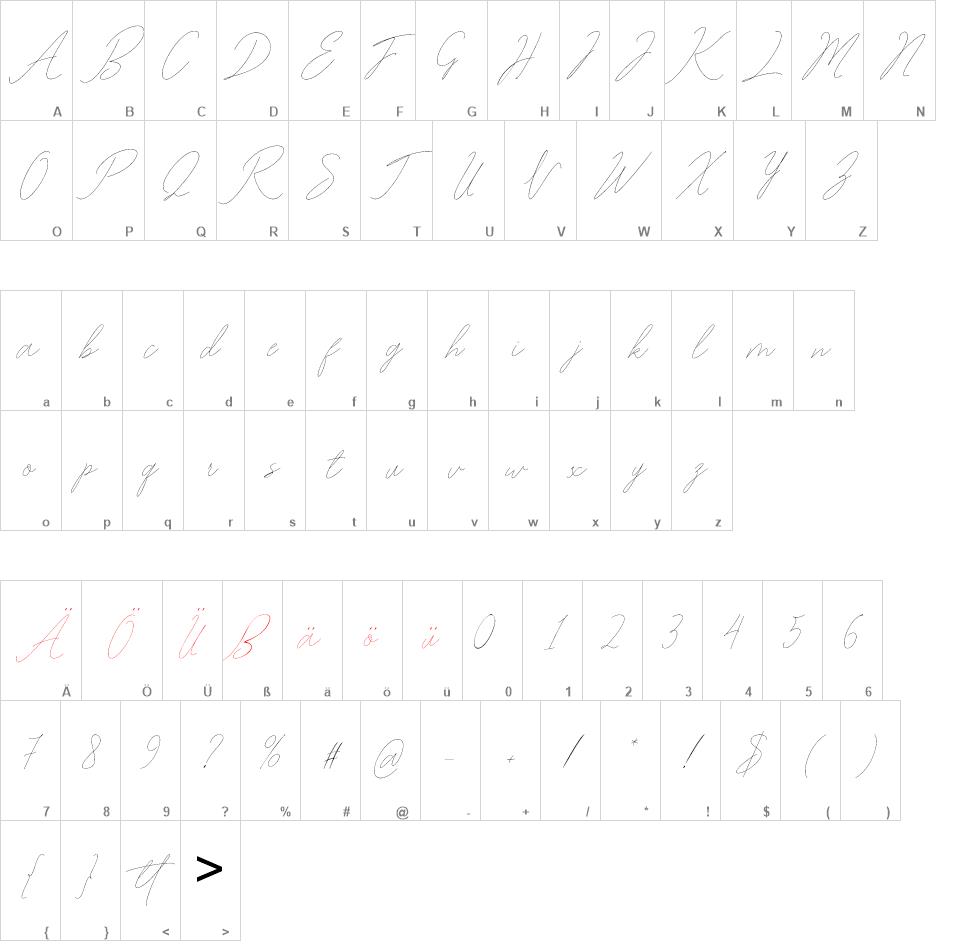
Washington
Washington font
Washington
Washington ist eine Unterschrift Schriftart, die die charakteristische Handschrift hat, ist es sehr geeignet, bestimmte Etiketten-und Event-Geschäft zu machen, und Sie könnten für ein einzigartiges Stück verwenden.